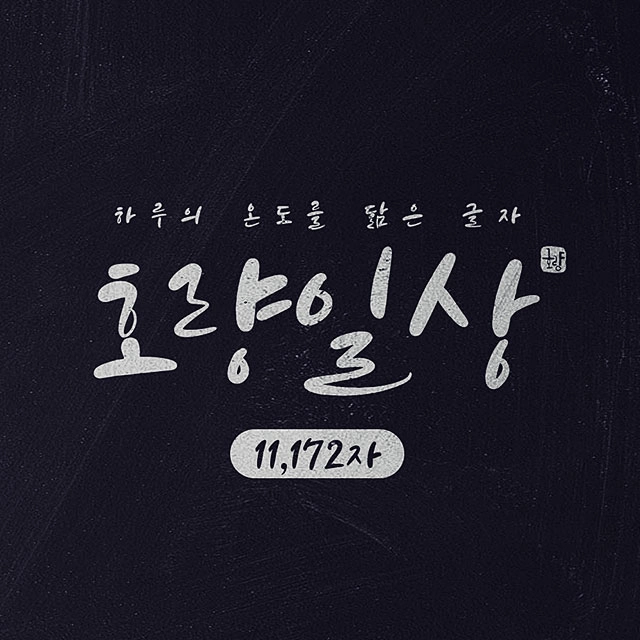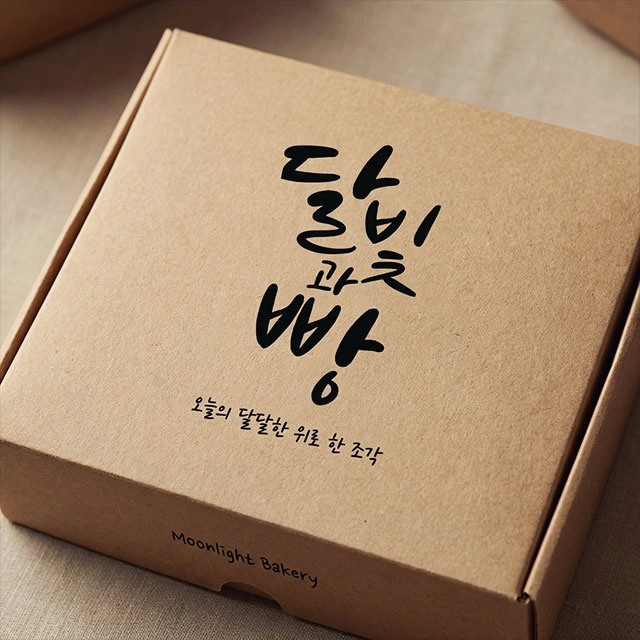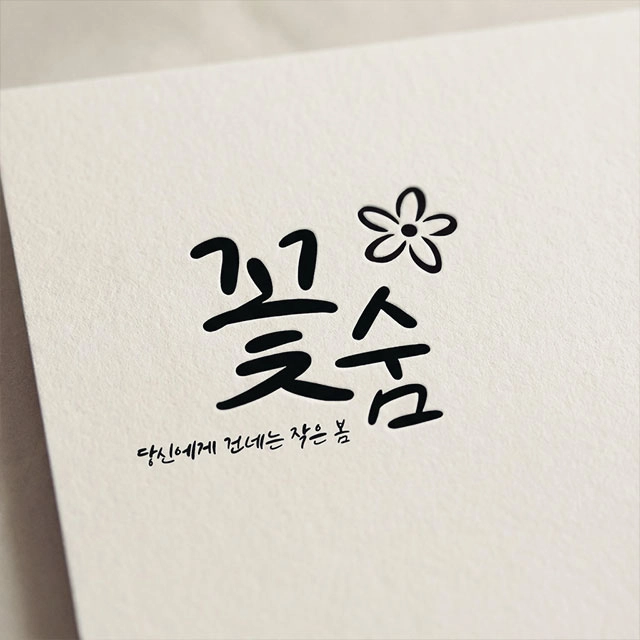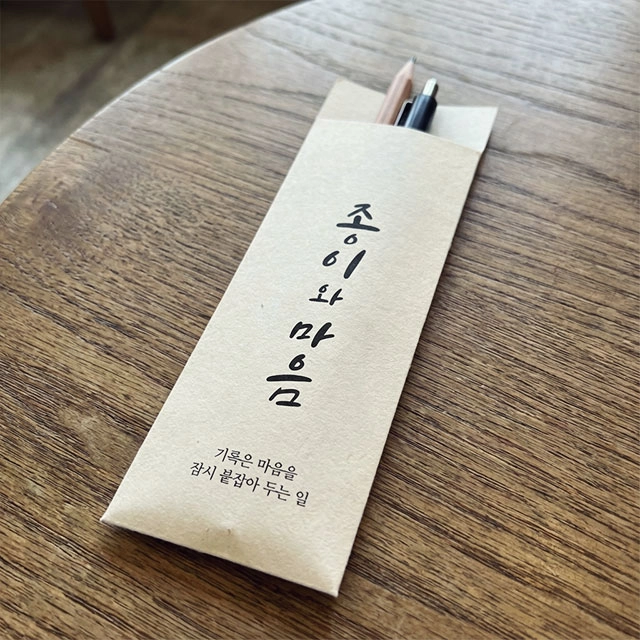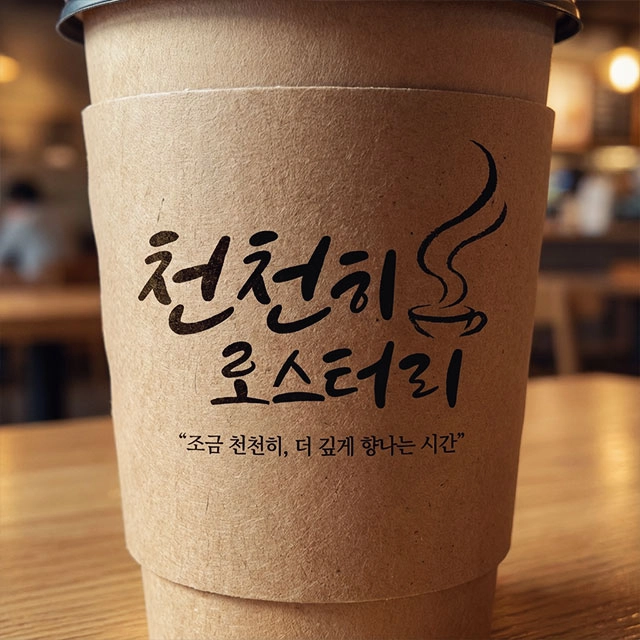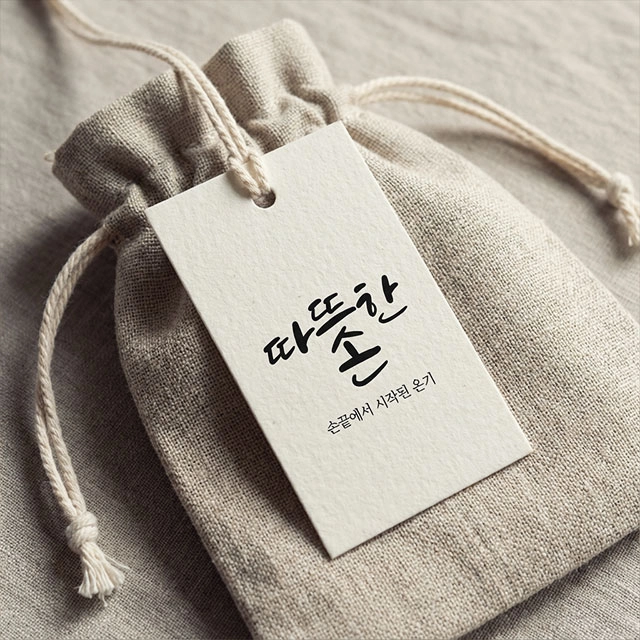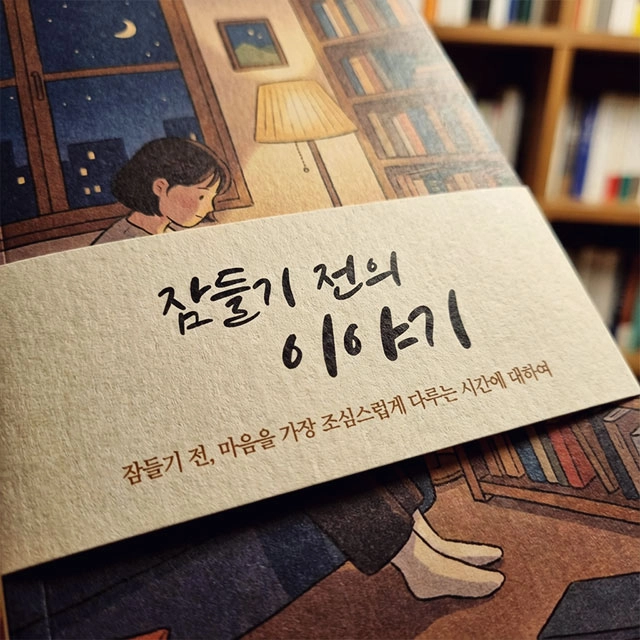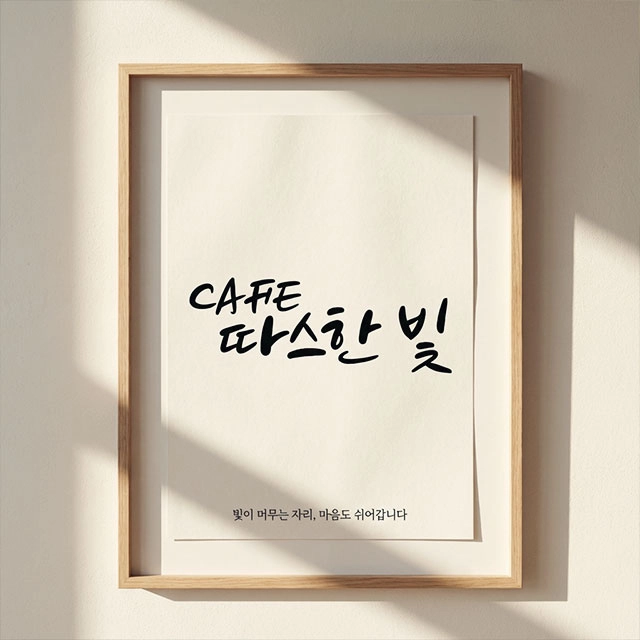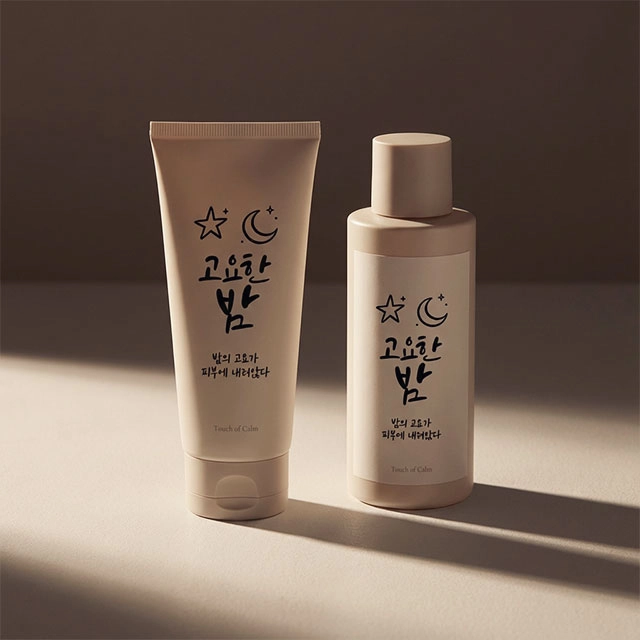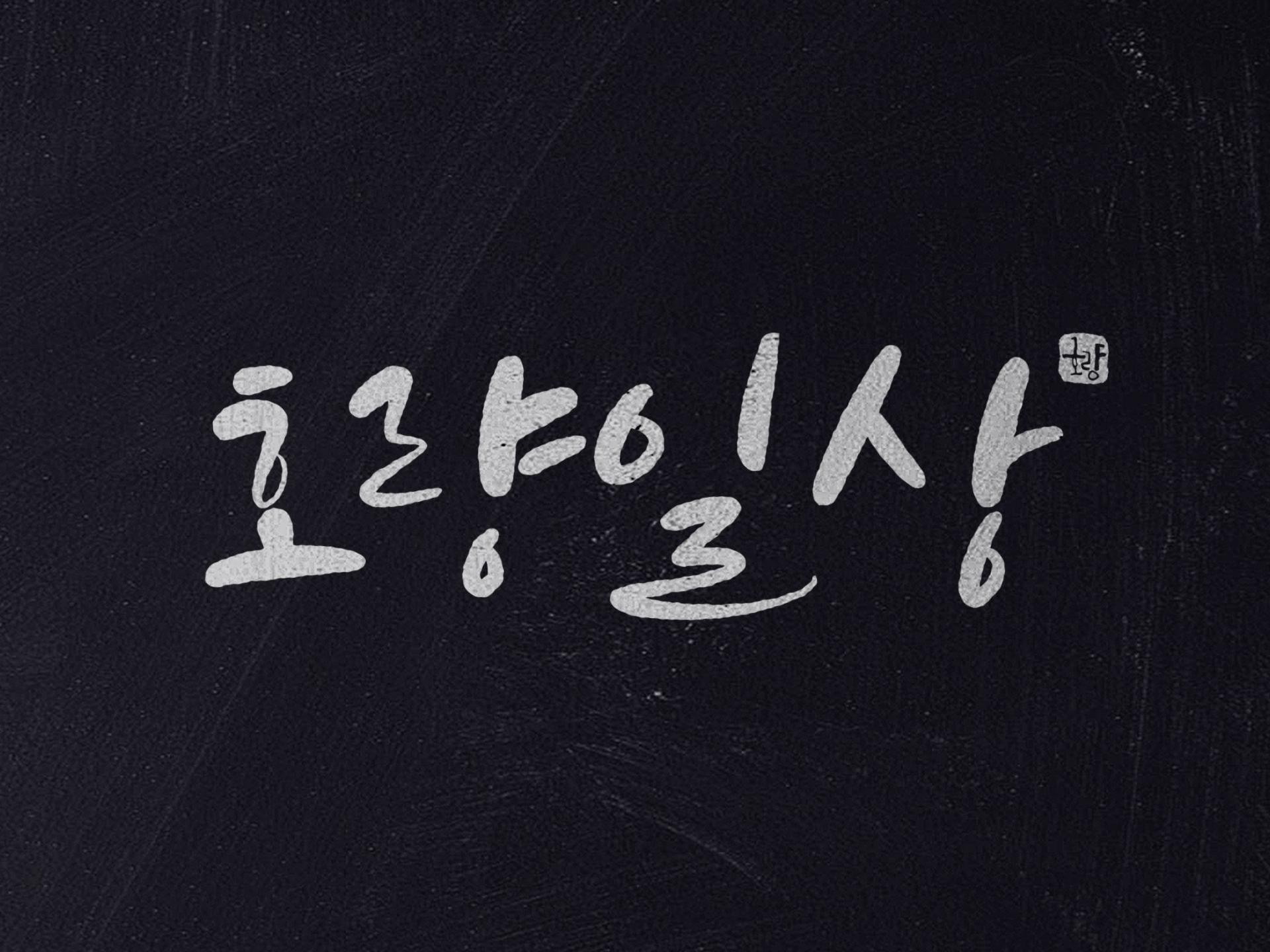
호량 일상
호량 작가의 다섯번째 감성 폰트, 떨리는 숨결이 남은 부드러운 곡선을 가진, 일상
한글 11,172자 / 영문·약물 94자
“손으로 쓰는 하루의 온도를 닮은 글자.” 호량 일상체는 캘리그래퍼 호량(Horyang) 작가가 매일의 기록 속 감정과 호흡을 그대로 담아 만든 손글씨 기반 캘리그라피 서체입니다. 힘을 주어 꾹 눌러 쓴 획, 떨리는 숨결이 남은 부드러운 곡선,
누군가에게 건네는 작은 메모처럼, 이런 분들에게 추천합니다 호량일상체는 말 그대로 일상에 감정을 담아 쓰는 분들을 위한 글자입니다. 꾸미지 않아도 자연스럽게 읽히는 손글씨, 딱딱한 글자보다 사람의 온기가 느껴지는 글씨를 원하는 분들께 추천합니다.
실사용 목업 예시 ① 베이커리 & 디저트 패키지 브랜드명: 달빛과 빵
② 꽃집 & 플라워 라벨 브랜드명: 꽃숨
③ 감성 문구·연필 세트 브랜드명: 종이와 마음
④ 로스터리 & 테이크아웃 컵 브랜드명: 천천히 로스터리
⑤ 핸드메이드 비누 / 홈케어 브랜드 브랜드명: 따뜻한 손
⑥ 독립출판 / 에세이 북커버 책 제목: 잠들기 전의 이야기
⑦ 카페 포스터 / 메뉴보드 브랜드명: 따스한 빛 카페
⑧ 화장품 / 스킨케어 패키지 브랜드명: 고요한 밤